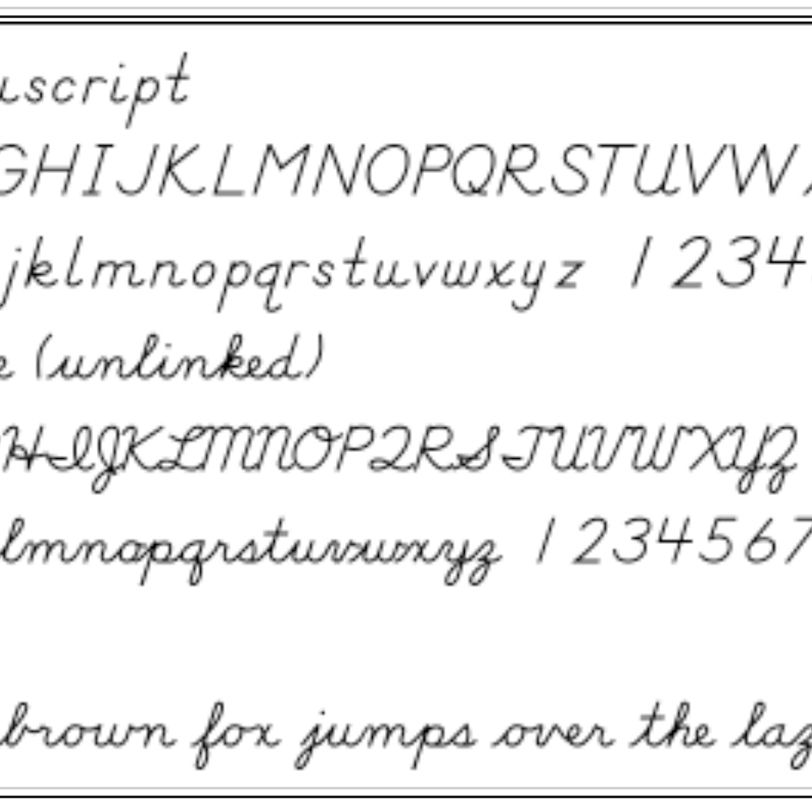
Дипломные и курсовые работы часто требуют сдавать в рукописном виде.
Это помогает преподавателям убедиться, что студент проработал материал, а не сдал текст, найденный в интернете, даже не просмотрев. Тем не менее, прогресс не стоит на месте, и появилось много приложений и сервисов, которые помогают перевести печатный текст в рукописный.
Писец 2.0
Это браузерный вариант имитатора рукописного текста. Вы его найдете, просто введя в любом поисковике запрос «писец». Можно конвертировать русский и английский текст.
Конвертер очень простой в использовании:
В левой части экрана введите печатный текст.
Нажмите кнопку «Перевести в рукопись».
В правой части экрана появится этот же текст в виде рукописи. Сохраните рукописный текст в формате PNG, кликнув правой кнопкой мыши и выбрав команду «Сохранить картинку как».
Плюсы:
Бесплатное использование.
Нет необходимости устанавливать программу.
Простой и понятный интерфейс.
Минусы:
Отсутствуют настройки – вы можете использовать только один почерк.
Невозможно создавать рукописи на тетрадных листах – вам доступен только белый фон.
Нельзя менять цвет ручки – доступен только стандартный синий цвет.
HandWriter
Конвертировать печатный текст в письменный можно с помощью смартфона. Для этого установите приложение HandWriter, доступное на Google Play.
HandWriter работает как с русскими, так и с английскими текстами, и весьма удобен в использовании. С его помощью можно преобразовывать конспекты из .txt и .docx в рукописный вариант, который выводится на печать в формате PDF (лучше загружайте файлы в Ворде, они гарантированно конвертируются без ошибок).
Также приложение работает с текстом, размещенным в таблицах.
Вы также можете напечатать нужный текст прямо в приложении, а затем скачать рукописный вариант текста в виде файла PDF.
Приложение позволяет:
Менять размеры страницы.
Настраивать угол наклона текста, размер шрифта, аккуратность почерка, отступы.
Добавлять новые шрифты.
Отображать рукописный текст на тетрадных листах в клетку, в линейку, или на фоне собственных загружаемых фонов.
Недостатки приложения:
нет возможности создать помарки;
нельзя сделать свой шрифт;
может выкидывать из приложения.
Программа активно разрабатывается, поэтому есть шансы, что в скором времени недочеты будут исправлены.
Синяк
Программа Синяк от Dimlight Studio предназначена специально для превращения печатного текста в письменный. Она устанавливается на ПК, и не имеет аналога для смартфона. Вы можете скачать ее бесплатно, введя в поиске «Синяк Dimlight Studio».
Программа позволяет:
Легко и быстро загрузить в программу собственный почерк.
Создавать текст, написанный некрасивым почерком, с помарками, что добавляет реалистичности.
Сохранять только текст, без фона (эффект прозрачности), что позволяет в дальнейшем накладывать текст на любой выбранный вами фон, используя в т.ч. другие приложения.
Использовать в качестве фона тетрадный лист в клетку, в линейку, в т.ч. двойные листа, а также загружать и использовать собственные фоны.
Имитировать текст, написанный карандашом.
Конвертировать тексты на русском, английском, а также украинском и белорусском языке.
Сохранять текст в формате PNG.
Программа идеально подходит для тех, у кого некрасивый почерк – большое разнообразие настроек позволяет превратить печатный текст в рукописный, причем с корявыми буквами, помарками, неровными строками, разным расстоянием между букв и слов, разной жирностью букв. Одним словом, увидев такой текст, человек никогда не догадается, что он напечатан на компьютере.
Минусы:
Без авторизации многие возможности программы заблокированы.
Вы получите полный доступ к программе только после авторизации на сайте производителя.
В программе сложно разобраться «методом тыка», поэтому рекомендуется просмотреть видеоурок, ссылку на который вы найдете на главном экране программы.
Fair Prosper
Это красивый шрифт, который, благодаря способу начертания букв, придаст элегантность любому проекту, который вы создадите. Это довольно красивый шрифт для рукописного ввода, который вы не должны исключать из своей библиотеки шрифтов.
Just Signature
Это еще один превосходно выглядящий рукописный сильный шрифт, который может стать ценным дополнением к вашей коллекции шрифтов. Невозможно оценить, сколькими способами этот шрифт может помочь вам в решении ваших задач.
В этом посте мы обсуждали шрифты, похожие на рукописный текст.